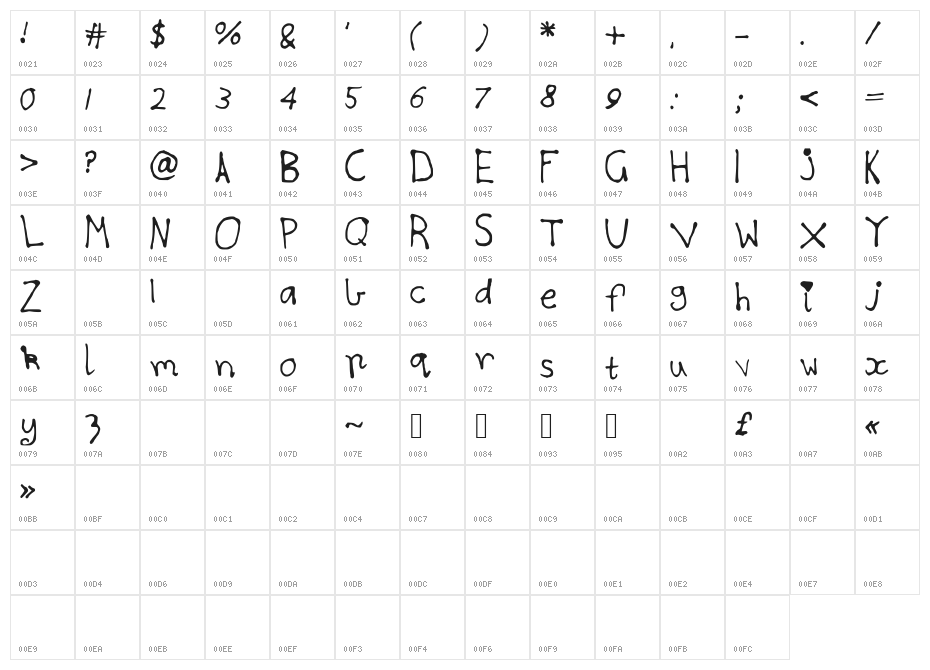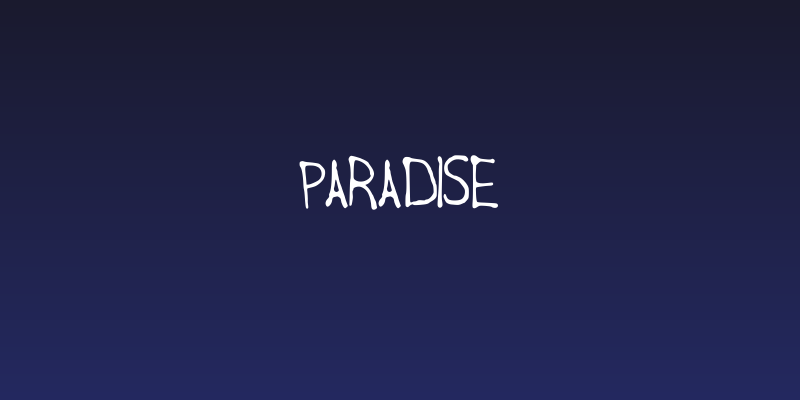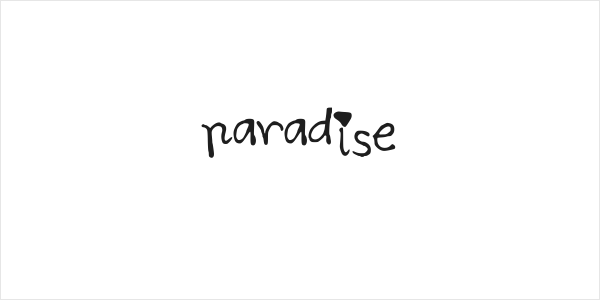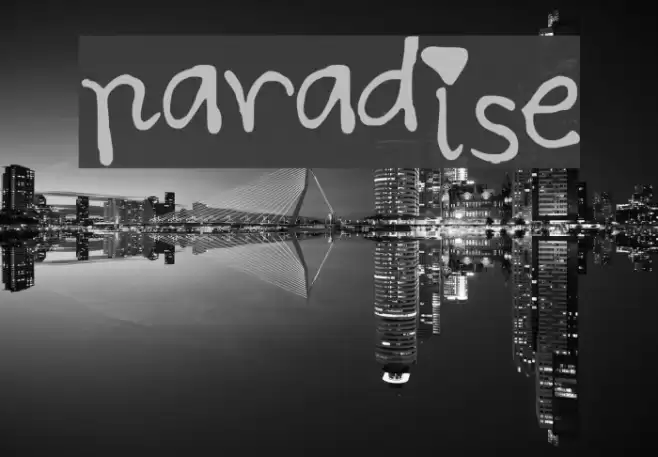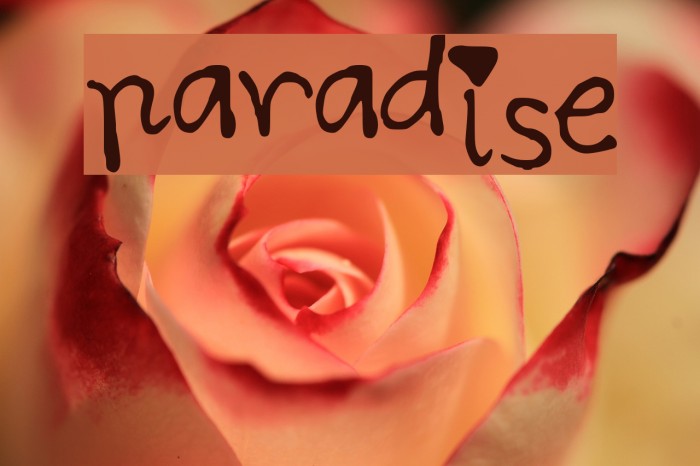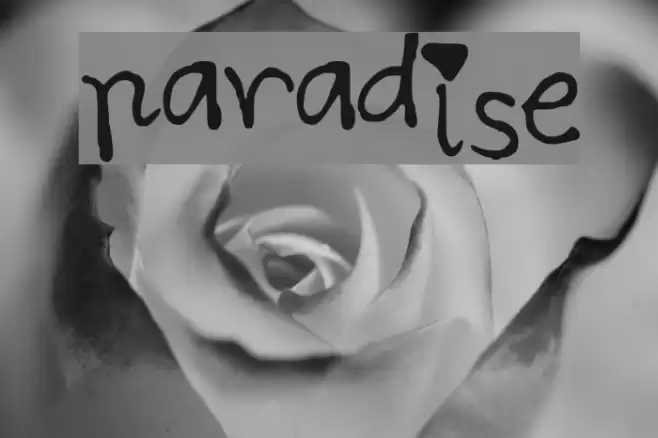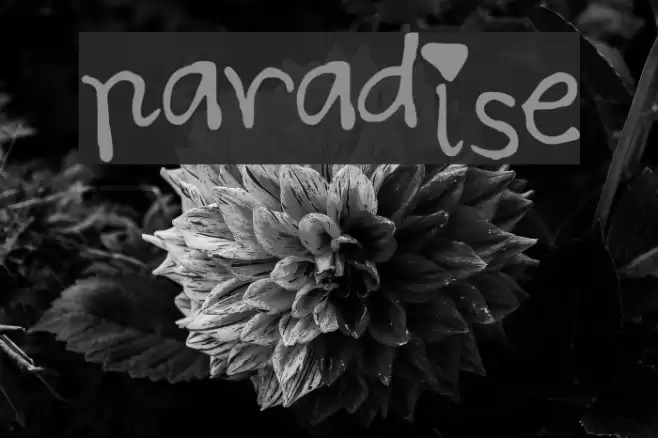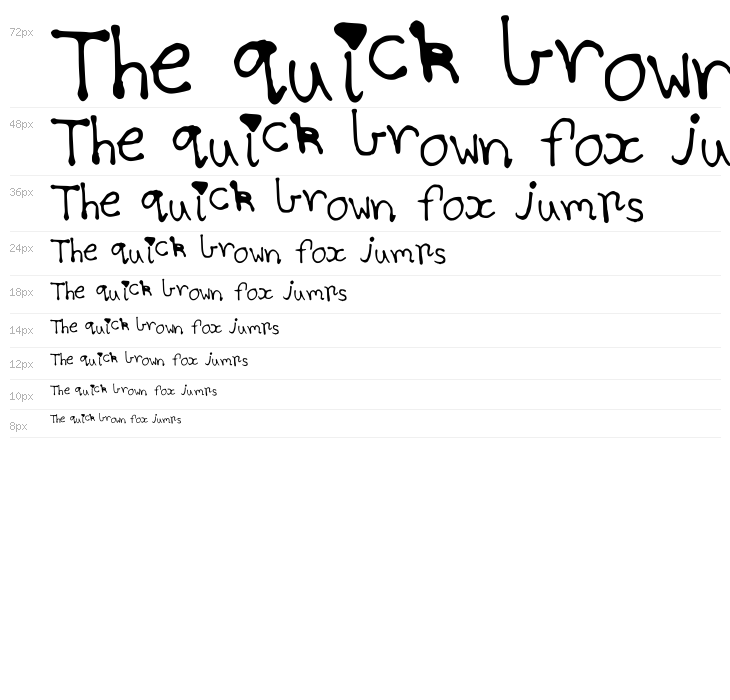
paradise Font
| Caso d'uso | Headlines, Logos, Informal Text |
| Progetti proposti | Ideal for children's books, greeting cards, playful branding, and casual invitations. |